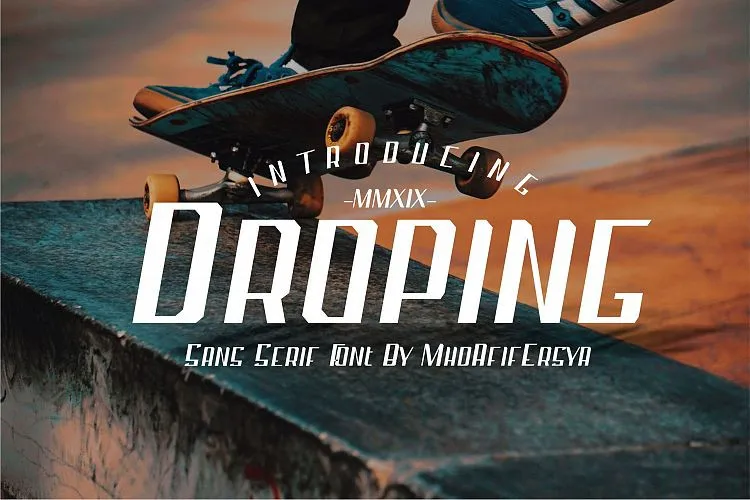
Droping Sans Serif Font – Download Grátis
Descubra seu próximo destino? Comece sua jornada! Introduzimos Droping Sans Serif Font para você. Esta novidade é uma tipografia esportiva, mas também perfeita para aquela delicadeza que você quer em suas cartas de convite ou painéis. Strong and clean, essa fonte moderna se adequa perfeitamente a logotipos, camisetas, roupas, citações escritas à mão, embalagens de produtos, cabeçalhos de pôster, materiais promocionais, etiquetas, marca e cartões de convite. Ela traz uma paleta de possibilidades para estilos diferentes. Seja ela um desafio ou uma brincadeira de palavras, Droping Sans Serif Font está aqui para ajudar a transformar suas ideias em realidade.